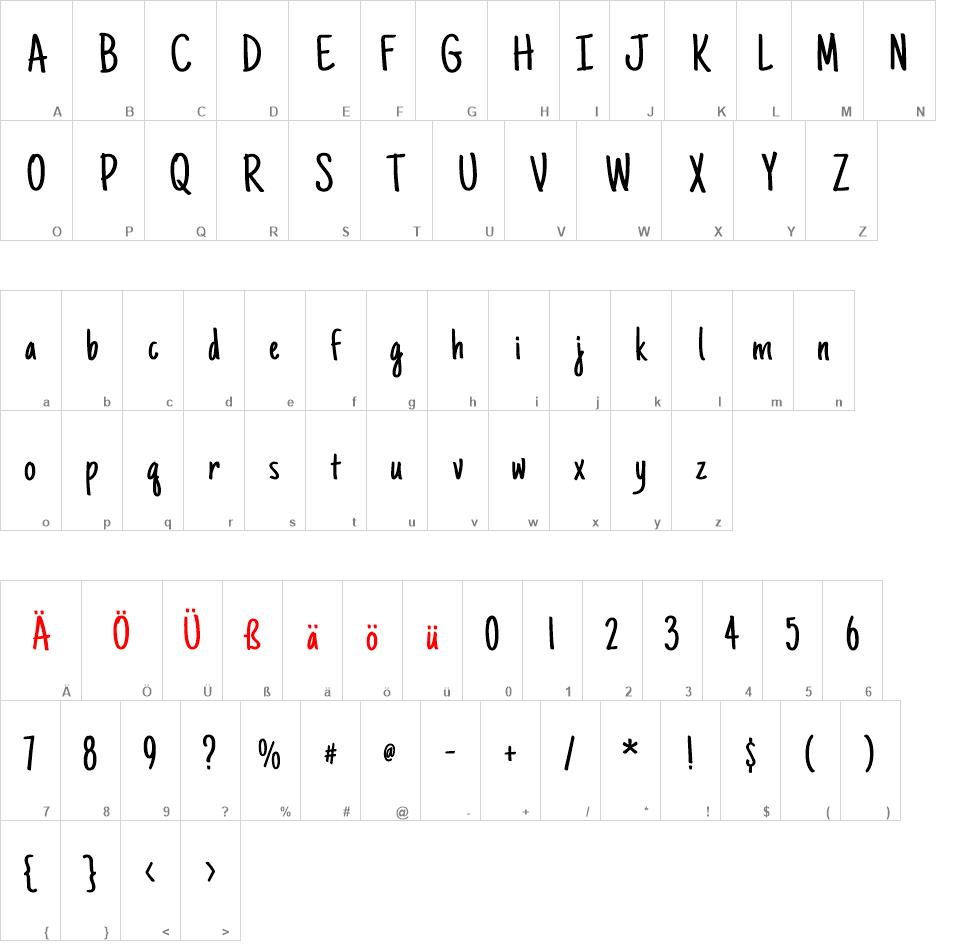
Just Another Hand Font
Unsere persönliche Handschrift hat sich im Laufe der Jahre oft verändert. Just Another Hand ist eine schmale, gebürstete, handgeschriebene Schrift, die von der Handschrift meiner Highschool-Tage inspiriert wurde. Ich habe es in der High School nicht mit einem Pinsel geschrieben, aber ich bekam eine kleine künstlerische Lizenz, die ich von einer anderen Elle erhielt, was bedeutete, dass ich einen saubereren Treffer für diesen Kommentar wollte.
Eine kleine Persönlichkeit, eine kleine Zurückhaltung ... ein Stil, der bei jeder Art von Projekt funktioniert.